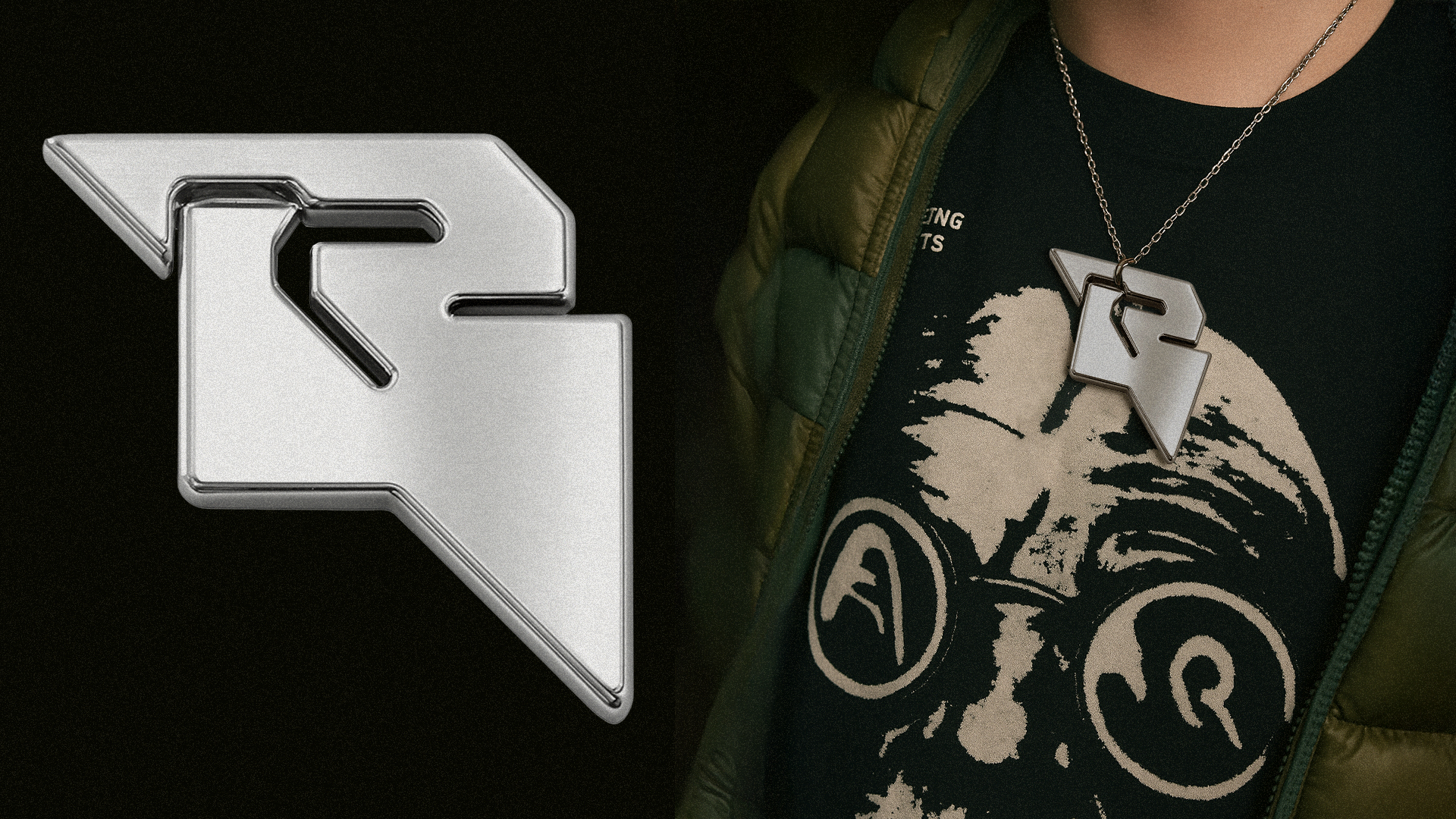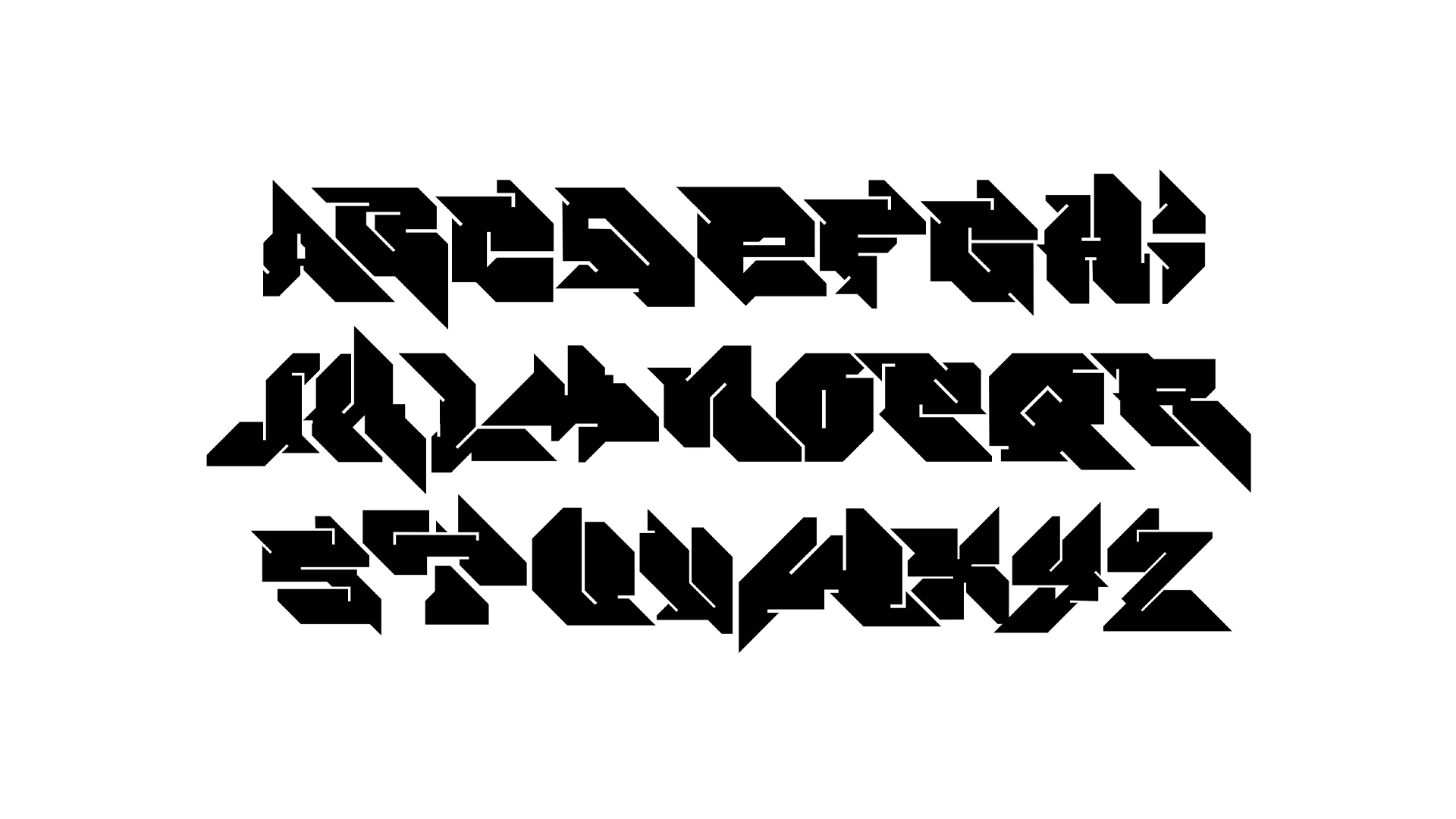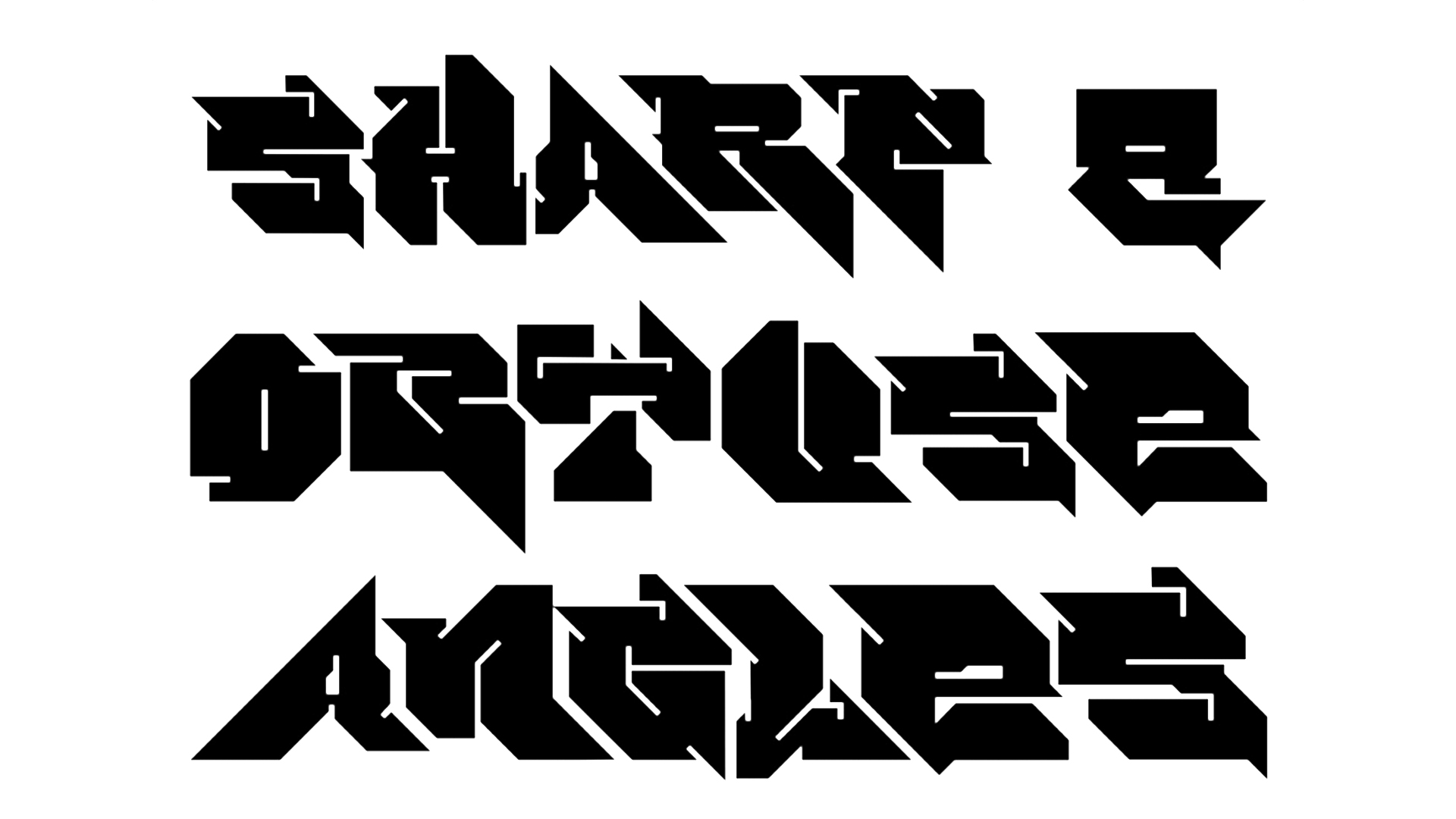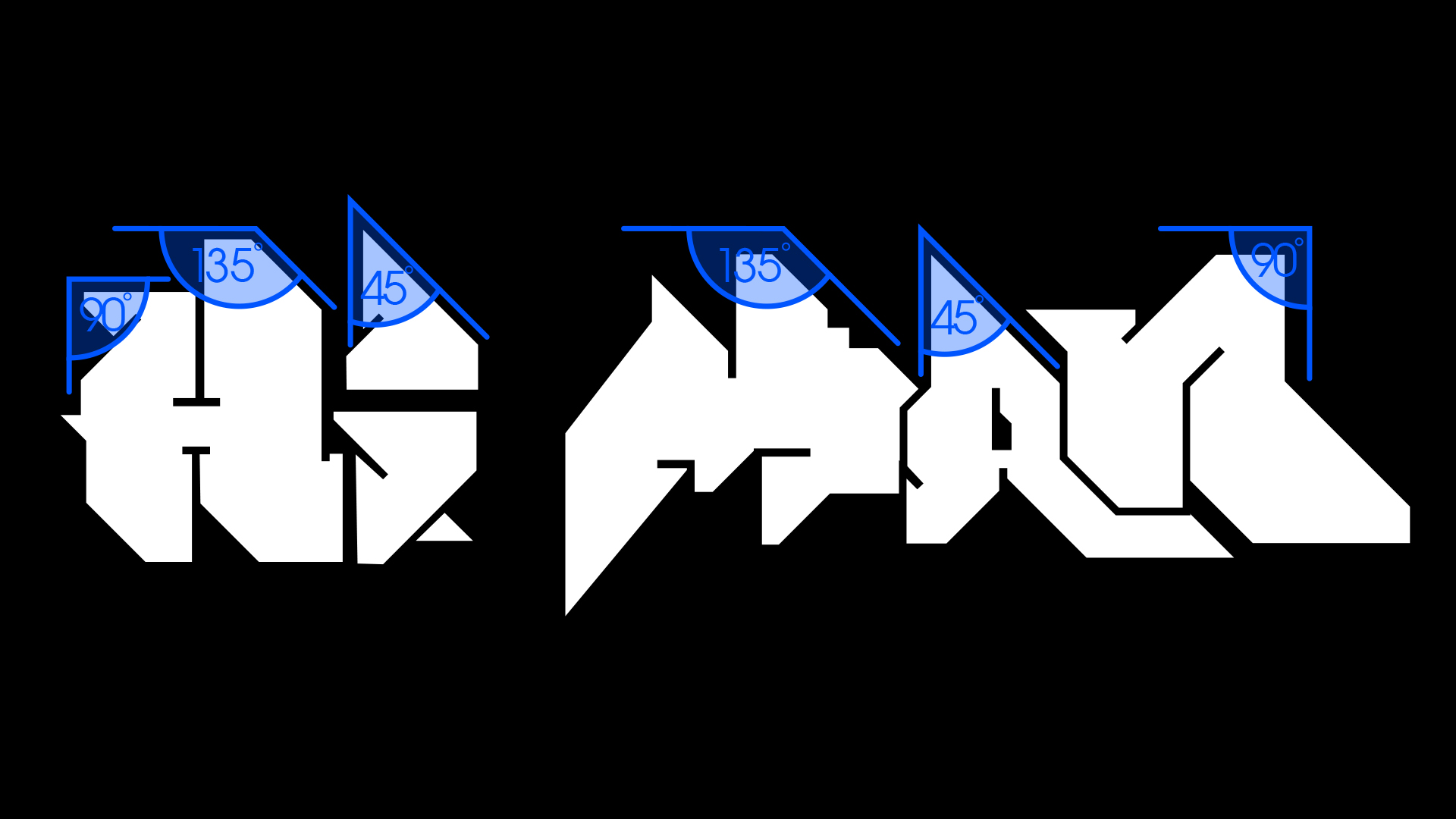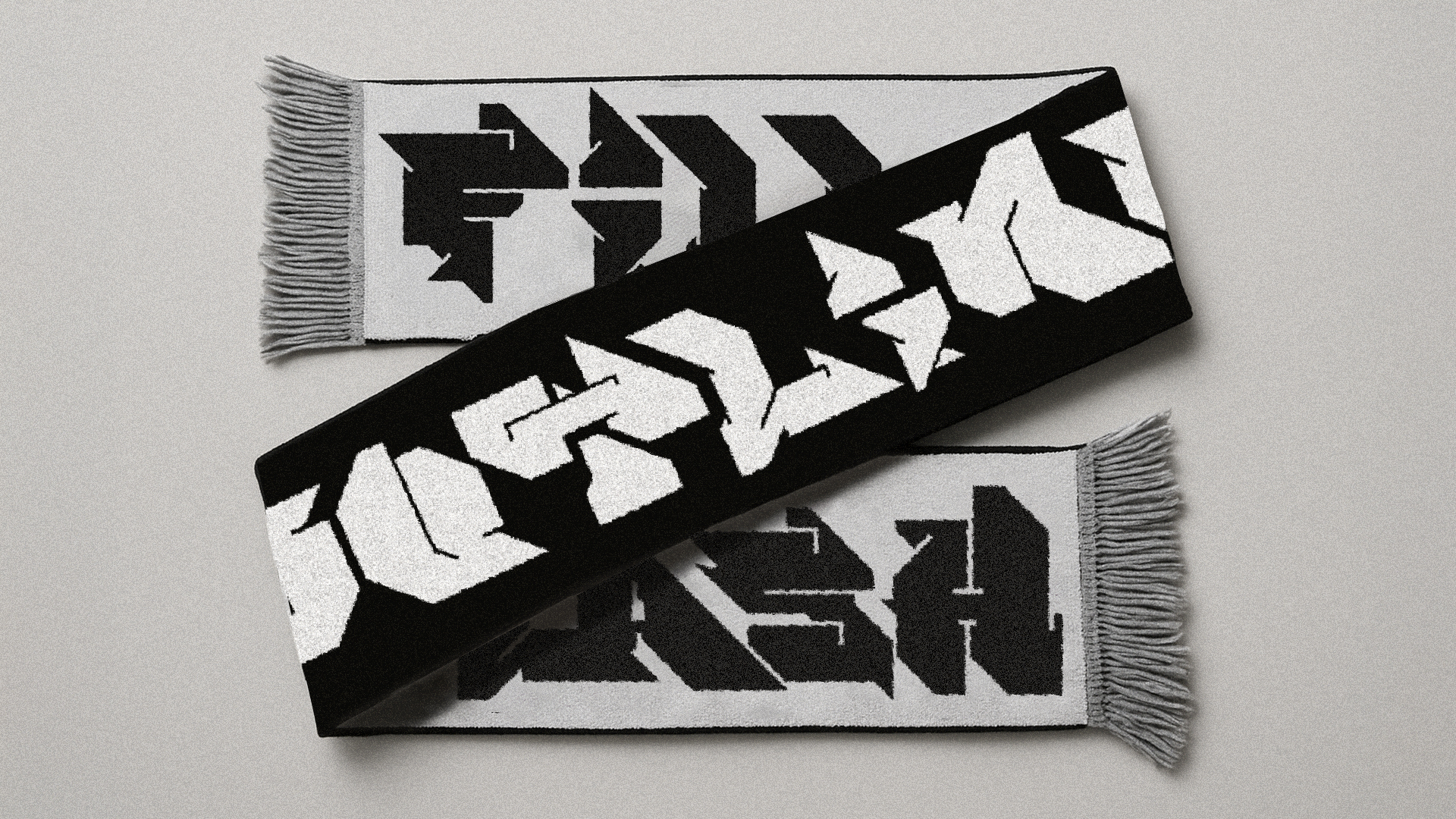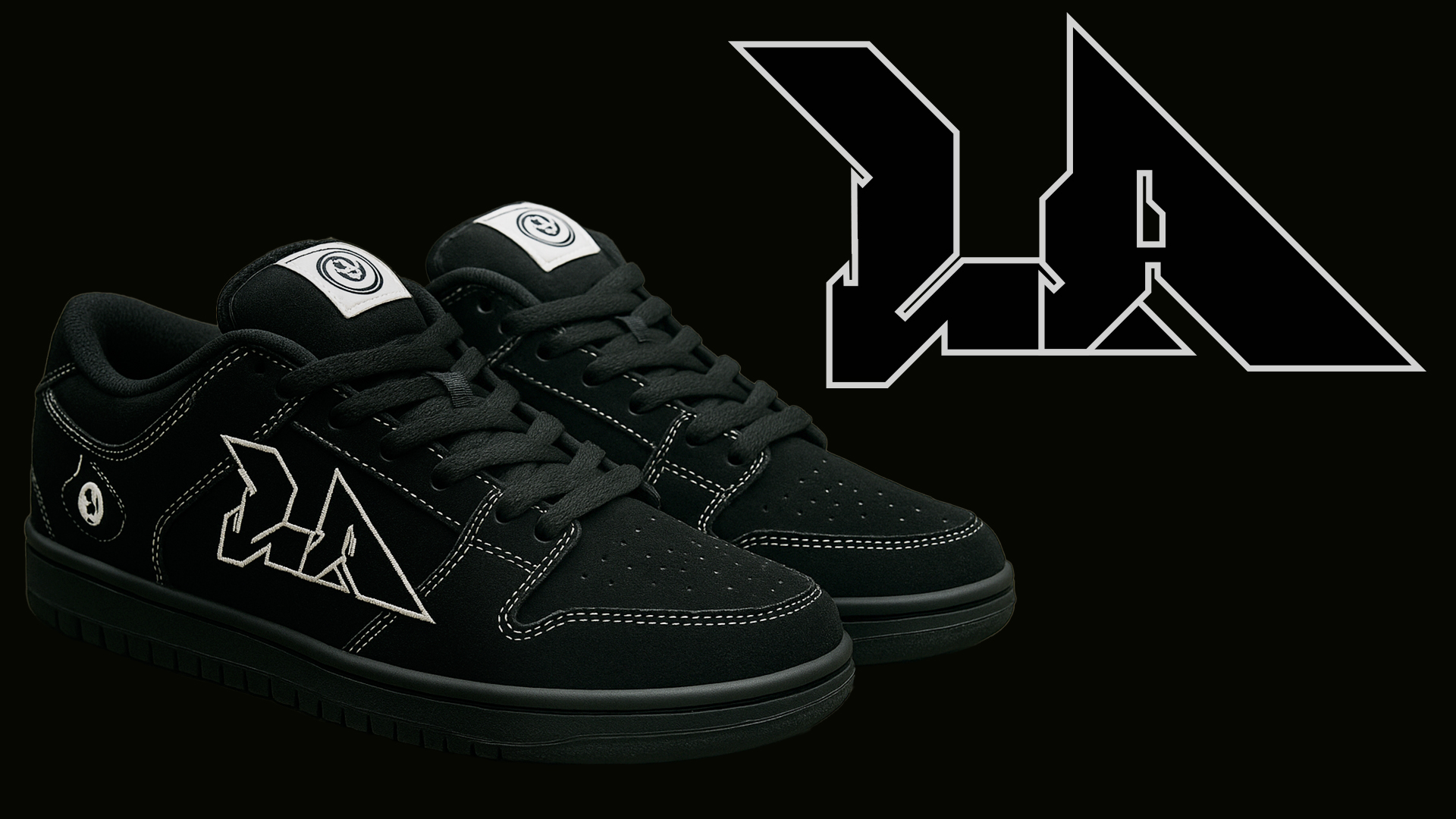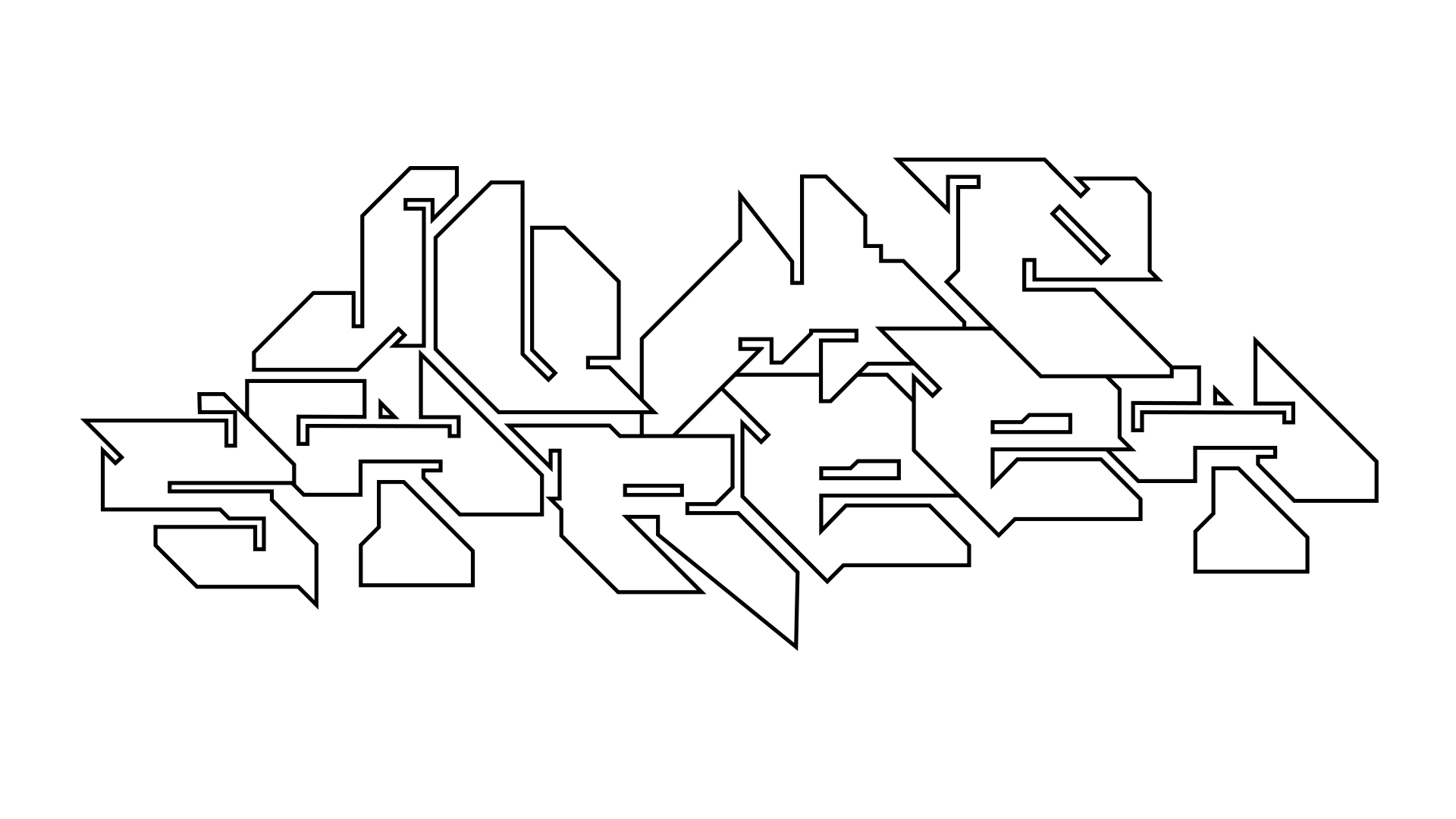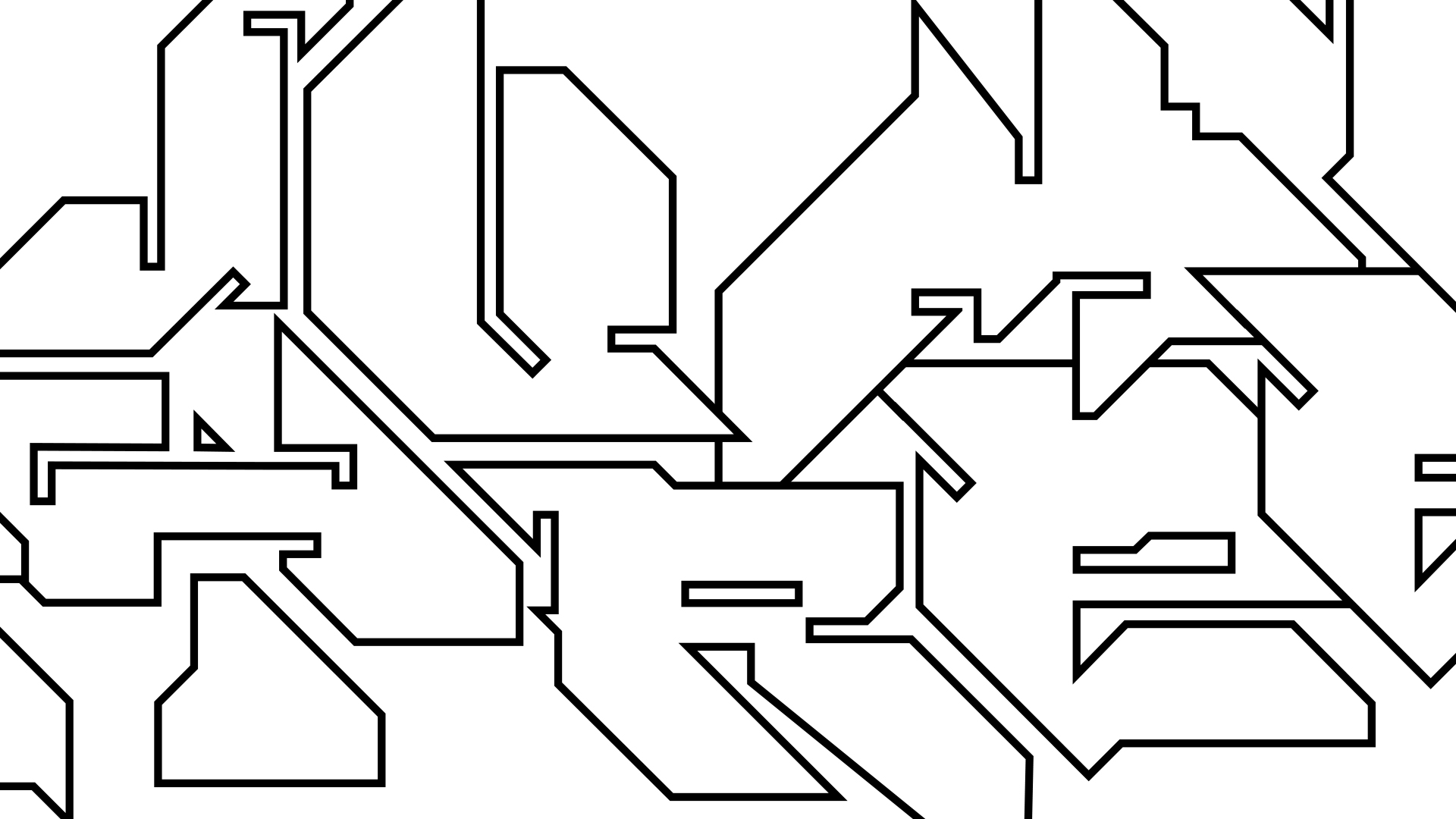
Экспериментальный шрифт
BAIS TYPEFACE
Описание работы
BAIS — граффити райтер из Краснодара. Его работы вдохновили меня на создание акцидентного шрифта.
Конструкция шрифта основана на углах 45°, 90° и 135°